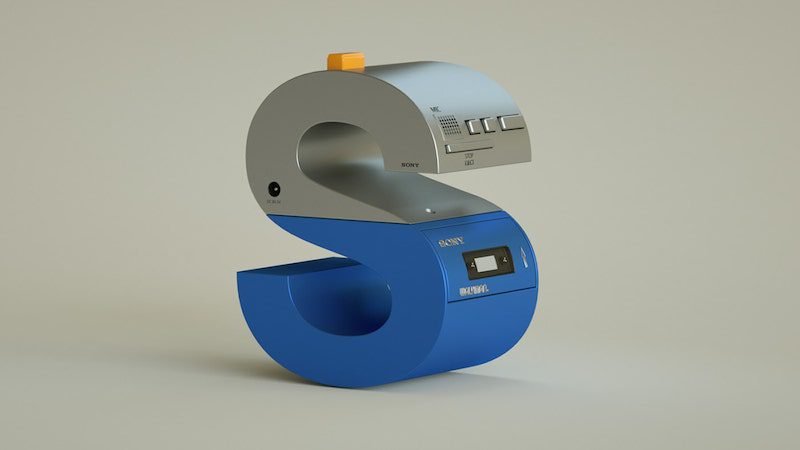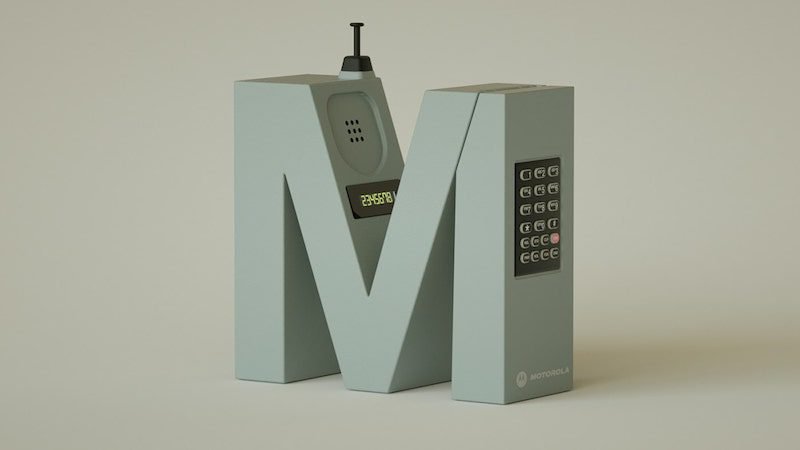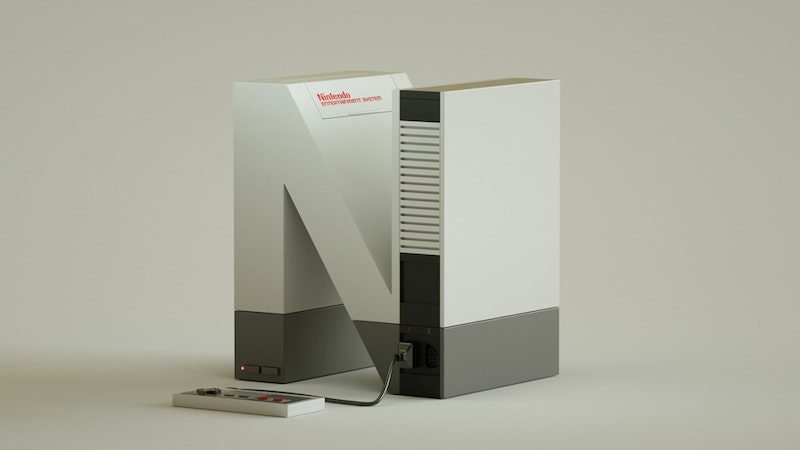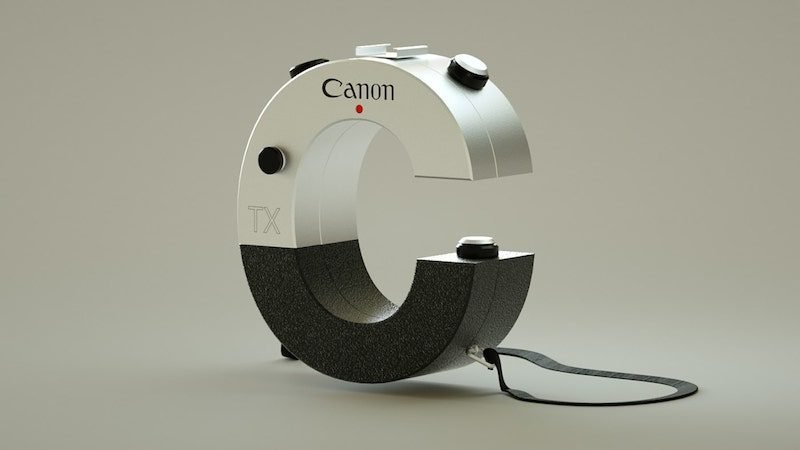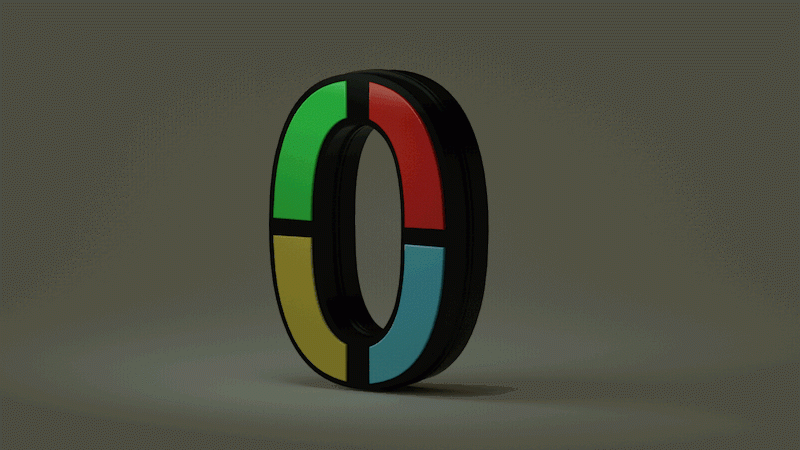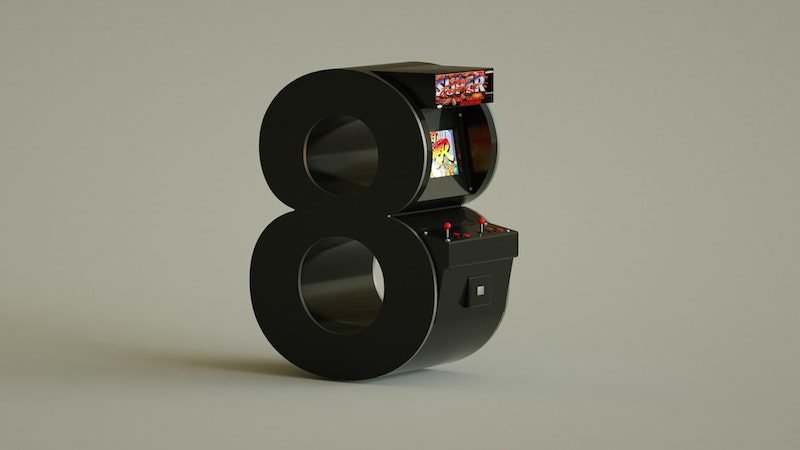
36 days electronics de Vinicius Araujo, 2017
36 Days Electronics, la tipografía retro de Vinicius Araujo
Diseño para los nostálgicos de las tecnologías
El diseñador brasileño Vinicius Araujo creó una tipografía retro y tridimensional basada en la fuente helvética e inspirada en los legendarios dispositivos electrónicos de fines del siglo XX. Desde el tocadiscos Technics SL-1200 (lanzado en 1972) hasta la cámara Canon TX (fabricada en 1975), pasando por el icónico teclado Yamaha o los míticos walkman de Sony, los añorados dispositivos han sido representados en el proyecto llamado 36 Days Electronics. Apple abre este recorrido retro con una de sus primeras computadoras personales materializada en una letra “A”, en la que el diseñador incluyó la ranura de la unidad de diskette y hasta un pequeño mouse. Los números también tienen destacados representantes, como el todavía vigente juego de mesa Simon creado en 1978, simbolizado con el número “0”, o la máquina de arcade del Street Fighter, con el “8”. Así, entre la nostalgia y el ingenio, 36 Days Electronics ofrece una vuelta al pasado a los amantes de los gadgets de finales del siglo XX.
36 days electronics, la tipografía retro de Vinicius Araujo
36 days electronics de Vinicius Araujo, 2017
36 days electronics, la tipografía retro de Vinicius Araujo
36 days electronics de Vinicius Araujo, 2017
36 days electronics, la tipografía retro de Vinicius Araujo
36 days electronics de Vinicius Araujo, 2017
36 days electronics, la tipografía retro de Vinicius Araujo
36 days electronics de Vinicius Araujo, 2017
36 days electronics, la tipografía retro de Vinicius Araujo
36 days electronics de Vinicius Araujo, 2017
36 days electronics, la tipografía retro de Vinicius Araujo
36 days electronics de Vinicius Araujo, 2017